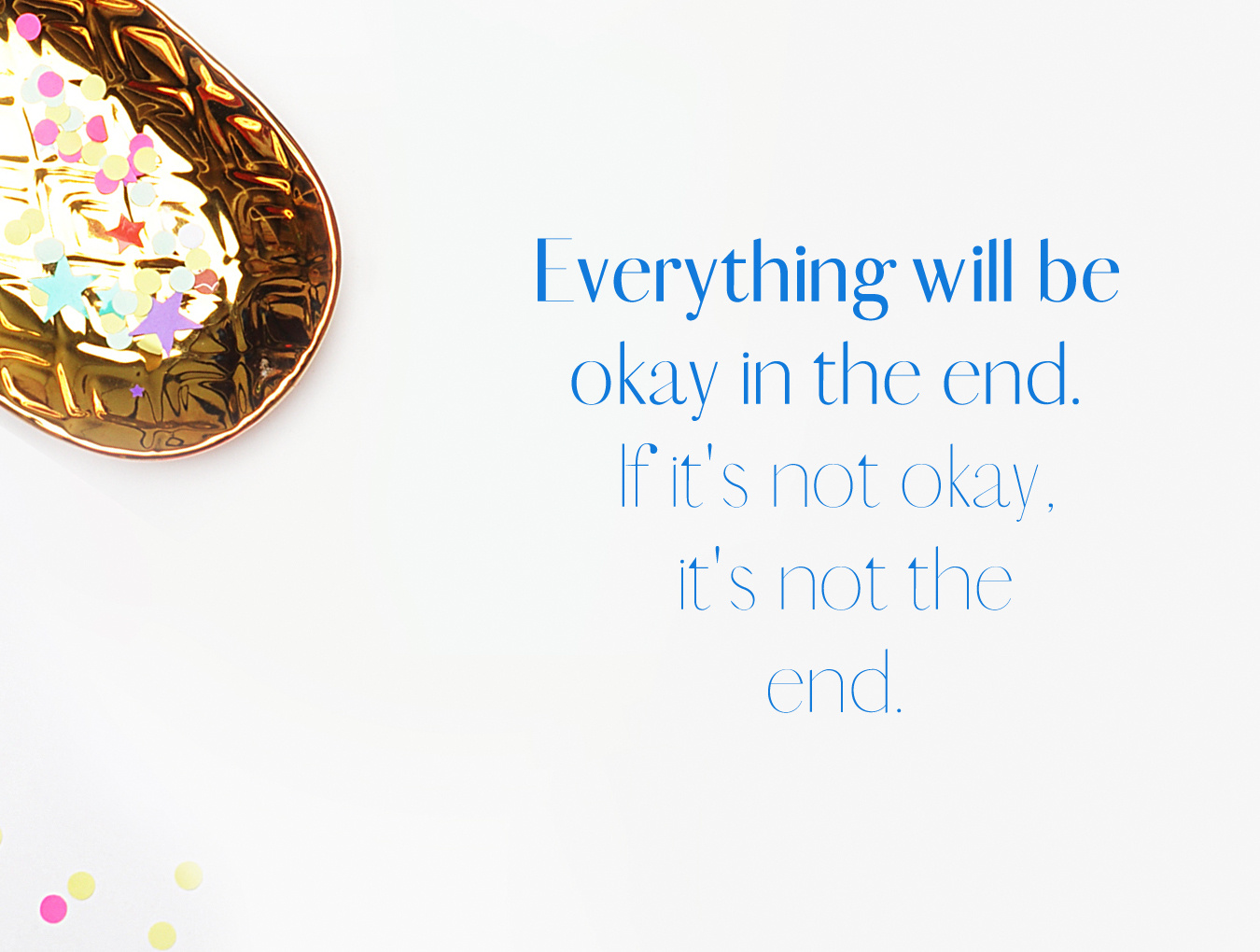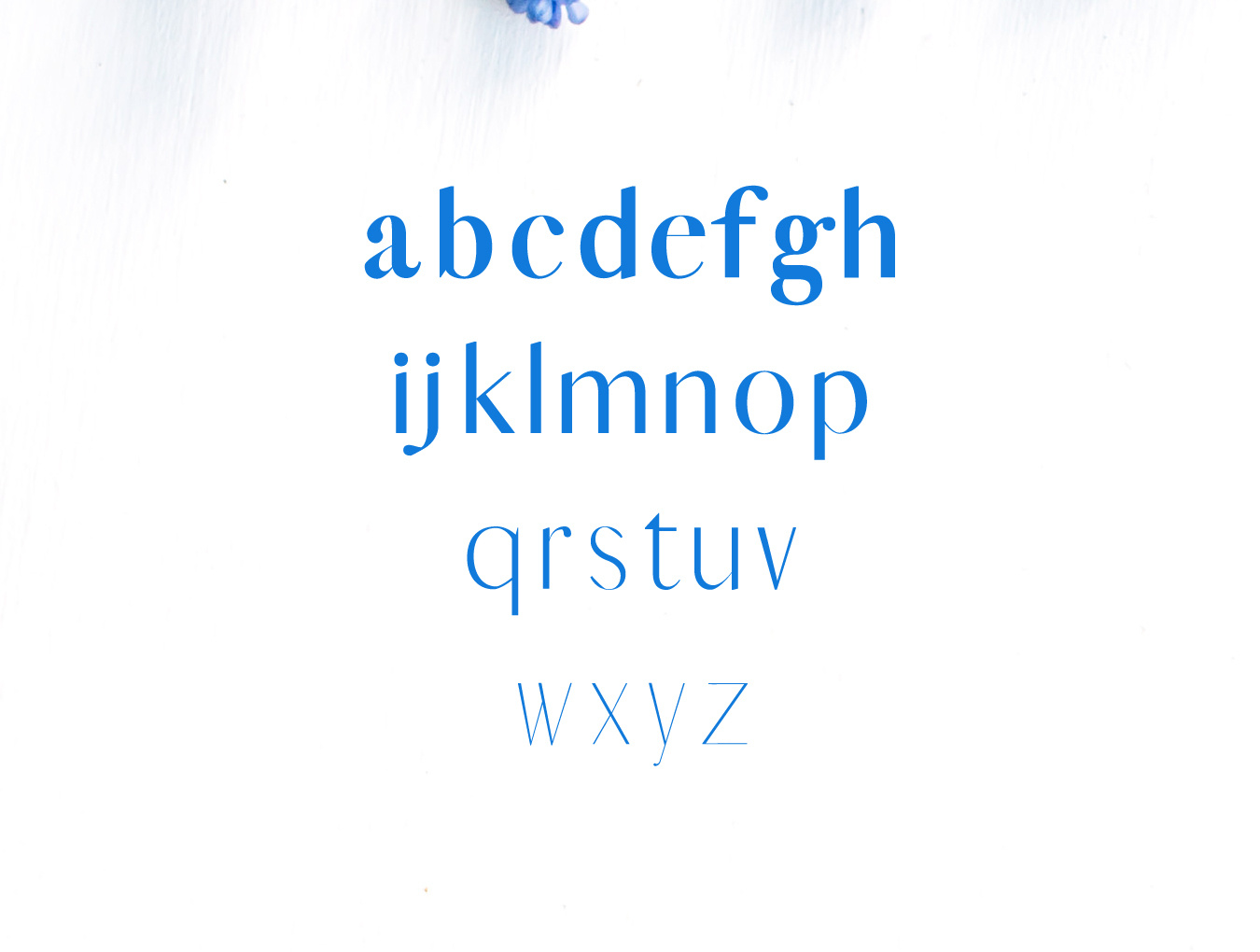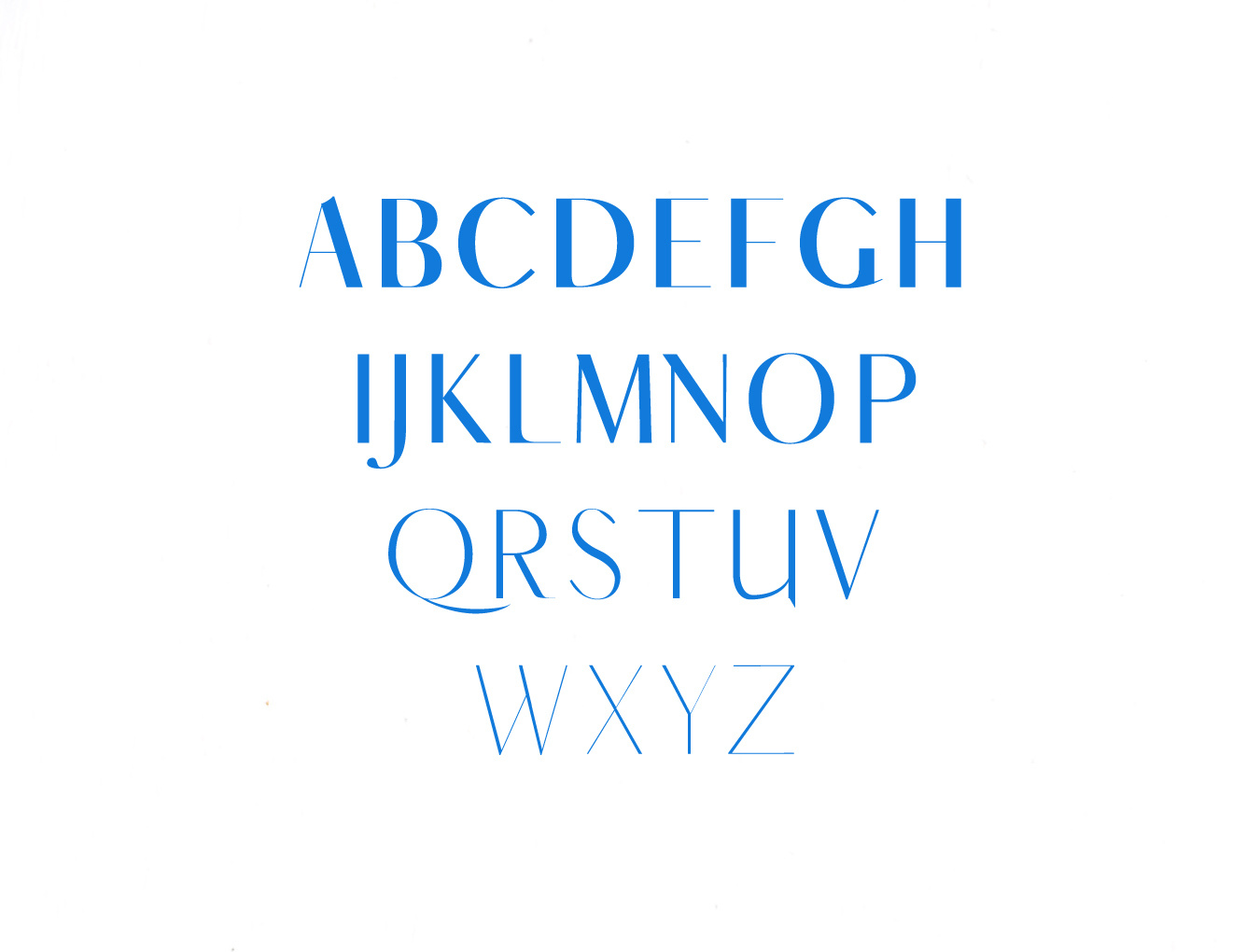
Adenn Sans Serif 4 Family Pack字体,Adenn Sans Serif字体
Adenn Sans Serif 4 Font Family Pack, Adenn Sans Serif Typeface
Adenn Serif字体是一个最小的干净无衬线字体系列,包含4个重量,它具有独特和现代无衬线的外观和感觉。非常适合华丽的徽标,标题,网页布局和品牌。如果你想尝试一个优雅的外观,它看起来华丽,所有帽子都有宽大的间距,或者在大写字母和小写字母中完美无瑕。